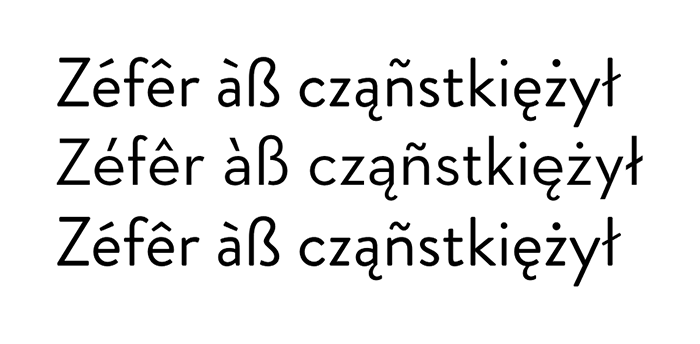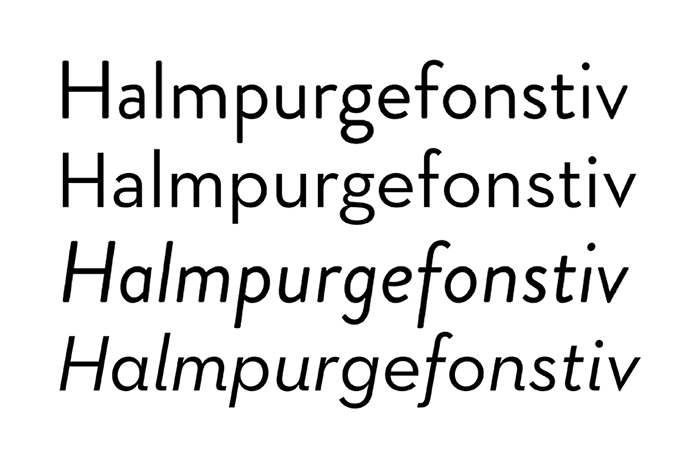
Welche Schrift ist das - oder welche ist ähnlich?
Die Avenir hatte ich letztes auch neu entdeckt, früher™ fand ich die nicht so toll :-?
Sicher weil sie Avenir heißt. ;-)
Auf dem ersten Blick gefällt sie mir ganz gut und sie ist ja auch ›bezahlbar‹.
Hast Du Dir die anderen fünf mal angesehen? Zu wenig gothamesk? :-)
Wenn Du die Wahl zwischen der Neutraface und Brandon Grotesk hättest, würdest Du Dich dann auch für die Neutraface entscheiden? Ich finde es schön, dass es dazu noch die passende Slab gibt. Auch sonst habe ich den Eindruck, dass man mir Ihr mehr anstellen kann. ;-):-P
hier mal ein kleiner vergleich von brandon grotesque (1. und 3. zeile) und neutraface 2 text für alle, die mitlesen, aber keine lust haben, sich selbst eine gegenüberstellung der beiden schriften zusammenzustellen:
ich finde die brandon grotesque eine schöne schrift und wäre auch nicht traurig, wenn ich mal aus irgendwelchen gründen damit arbeiten müsste – aber so richtig verlieben kann ich mich in sie nicht. ich finde die unterlängen zu lang und die versalien vor allem in der aufrechten zu breit. da der gestalter deutscher ist, wird er schon wissen, was er tut – oder er richtet sich an ein publikum, das eine weniger versalienlastige sprache als deutsch setzt. auf mich wirkt die brandon jedenfalls displayiger als die textschnitte der neutraface. ein plus dieser textschnitte ist meiner meinung nach, dass sie kapitälchen mitbringen, die die brandon nicht hat. außerdem bin ich zugegebenermaßen sehr eingenommen von diesen kalligrafisch angehauchten abstrichen in der kursiven neutraface. mit der slab-variante habe ich leider noch nie gearbeitet, aber auf mich macht sie einen ebenso soliden eindruck wie die sans. und dann gibt es ja in beiden fällen noch explizite display-schnitte, die recht schick sind.
und noch ein letztes: mein blick fällt auch immer darauf, wie diakritika für sprachen, mit denen ich häufiger in berührung komme, ausgearbeitet sind. da gefällt mir die neutraface (auch) deutlich besser:
die akzente hängen in der brandon ziemlich hoch (was ich in der untersten zeile zum spaß zu korrigieren versucht habe). ›ß‹ (sehr breit), ›ę‹ (ogonek wie angeklebt) und ›ł‹ (warum ist der querstrich so dünn?) machen auf mich auch einen weniger überzeugenden eindruck. in einem beispiel mit nonsenswörtern wirkt es vielleicht korinthenkackerisch, so was zu kritisieren, aber wenn man einen ganzen, sagen wir, französischen text mit solchen schwebeakzenten vor sich hat, wirkt das eher befremdlich. mein votum also: neutraface :-D
Sicher weil sie Avenir heißt. ;-)
Hast Du Dir die anderen fünf mal angesehen? Zu wenig gothamesk? :-)
Also, ich suche ja eigentlich gar nicht, mir gefiel die nur auf anhieb. Die Centrale ist ja auch ganz hübsch, aber für mal eben so wieder etwas teuer und die Kursive, die mir bei der Gibson sehr gefällt, finde ich etwas ›sperrig‹.
Eine Condensed oder so, finde ich für eine Arbeitstier-Schrift gar nicht so wichtig ...
Ich vermute, Robert meint die "Zukunft" als Übersetzung für Avenir, wenn man es als französisches Wort ansieht.
Das ist schon ein Fuchs, der Herr Adrian – und seiner Zeit weit voraus. Das meine ich ganz unironisch ... :nicken:
Das ist schon ein Fuchs, der Herr Adrian – und seiner Zeit weit voraus.
Das habe ich auch gedacht. Und irgendwie werde ich seiner (Grotesk)Schriften nicht überdrüssig. Also ich rede jetzt mal von Avenir, Univers und Frutiger. Auch wenn mir nicht alle zu hundert Prozent gefallen, würde ich dennoch behaupten, dass sich keine von Ihnen so wirklich abnutzt. Vielleicht liegt es daran, dass sie alle drei eher von bescheidener Natur sind. Beeindruckend.
Eben gefunden, der letzte Absatz ist selbstredend:
Im Blei habe ich die Schrift und ihre Fähigkeit, mit immer denselben Lettern die ganze geistige Welt lesbar werden zu lassen, zuerst erlebt. Damit erwachte in mir das Bedürfnis, die bestmögliche Lesbarkeit zu entwickeln. – Schnell kam die Zeit, in der ein Text nicht mehr mit Bleibuchstaben, sondern durch einen Lichtstrahl gesetzt wurde. Die Aufgabe, die Schriften der alten Meister vom Hoch- in den Flachdruck umzudenken, war für mich die beste Schule. Als es jedoch um den Grotesk-Stil ging, hatte ich meine eigene Vorstellung: es enstand die Univers-Familie. Die technischen Fortschritte gingen rasch voran. Die elektronische Bildübertragung brachte die Verzackung und später die Vektorisierung der Umrisse. Für mein Formengefühl war das eine Leidenszeit. Doch heute, mit Kurvenprogrammen und Laserbelichtung, scheint mir, dieser Weg durch die Wüste sei zu Ende gegangen. –
Aus allen diesen Erfahrungen habe ich als Wichtigstes gelernt, daß Lesbarkeit und Schönheit ganz nahe beieinander stehen und daß die Schriftgestalt in ihrer Zurückhaltung vom Leser nicht erkannt, sondern nur erfühlt werden darf. Die gute Schrift ist diejenige, die sich aus dem Bewußtsein des Lesers zurückzieht, um den Geist des Schreibenden und dem Verstehen des Lesenden alleiniges Werkzeug zu sein.
Eine Condensed oder so, finde ich für eine Arbeitstier-Schrift gar nicht so wichtig ...
Das hängt wahrscheinlich auch davon ab, für welche Arbeit man das Tier einspannen möchte. Bei den letzten CDs kam ich an passenden Condensed-Schnitten nicht mehr vorbei und habe solche Großfamilien inzwischen sehr schätzen gelernt. :-)
und wo wir beim thema gothamesk sind:
ich werf mal noch schnell die GT Walsheim in die runde. habe ich gerade beim kollegen
koeberlin entdeckt und gefiel mir auf den ersten blick recht gut.
an die brandon grotesk komme ich überhaupt nicht ran, schon allein diese rundgelutschten
enden, ich versteh nicht was dieser font sein will. an der brandon gibt es zuviel details, die
mir jedesmal aufs neue schlecht ins auge fallen.
Die Superla kannte ich zwar schon, finde ich aber auch nicht schlecht.
Ganz lieben Dank Thierry! Habe mir nun mal etwas Zeit nehmen können, Deinen Vorschlag genauer anzusehen. Ich glaube die Proxima Nova ist genau das, wonach ich so lang gesucht habe. :biglove: